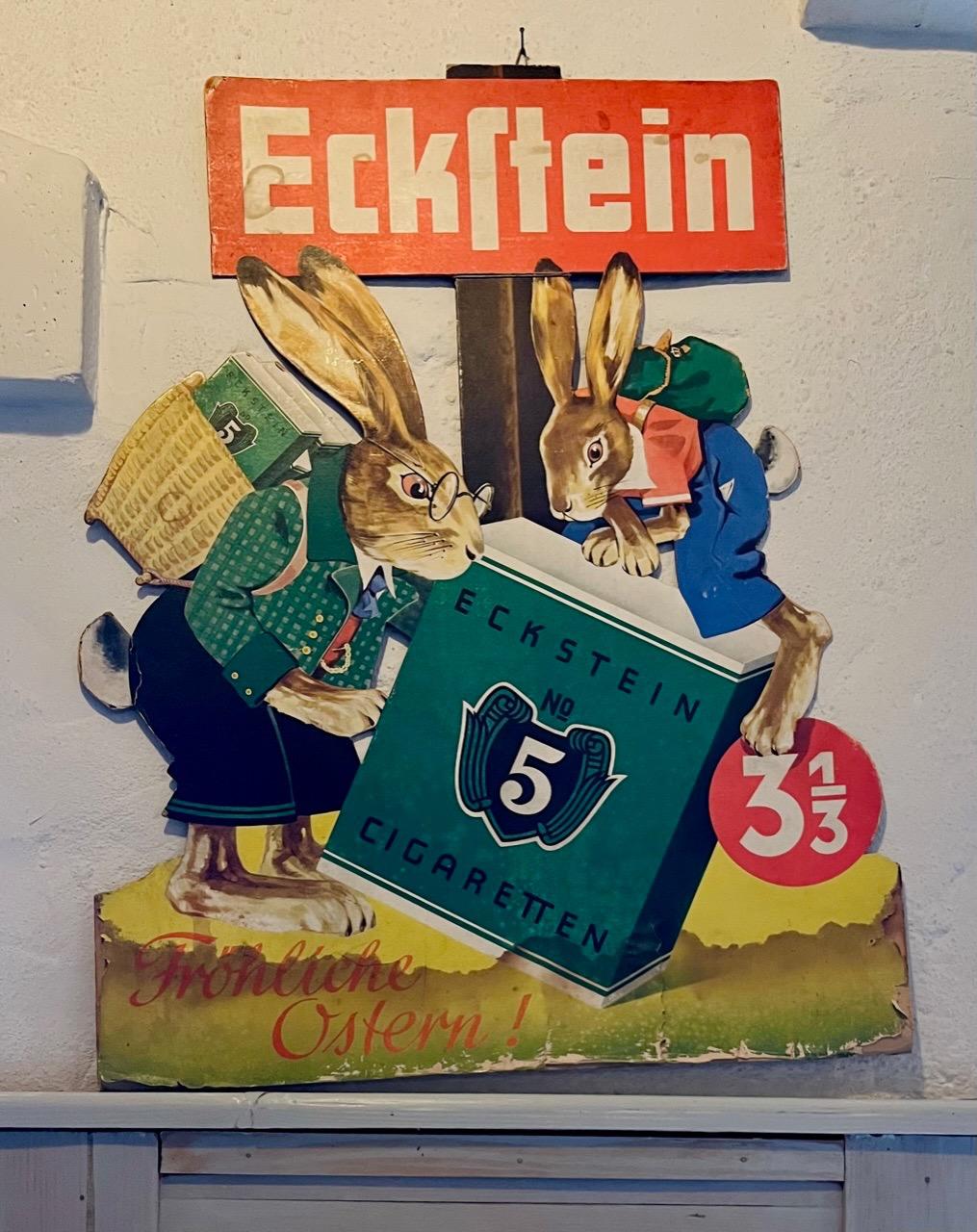
Die Verwirrung ist ganz in meinem Kopf.  Ich habe die echt unter Selectrix abgespeichert. Ich meine natürlich die IBM Selectric 😊
Aber vielleicht macht sich so ein Kugelkopf auch in einer Modellwelt ganz gut.
Fröhliche Ostern!
Eckstein. Das war schlimmes Zeug ohne Filter. Ich hatte mal einen Vermieter in den 90ern. Der hat davon viel geraucht, das war über Stockwerke kaum auszuhalten. Eckstein war damals angeblich schon schwer zu bekommen.
Eckstein gab es wohl noch bis 2015. Ich hab in meiner Jugend in den 1990ern auch mal ne Packung gekauft — aber das war ähnlich starker Tobak wie Karo.
Sind nun nicht alle wahnsinnig spannend, ich fand die Visitenkarten trotzdem ganz interessant. Auch wegen der Notizen …
Nachtrag: Die Visitenkarten waren in einer Ausstellung im Metropolitan Museum of Art / NY zu sehen (außer Warhol und Ed Ruscha).
Warum hier keine einzige Künstlerin vertreten ist, ist nachvollziehbar wohl der Zeit / dem Umstand geschuldet, dass die meisten vor dem 20. Jh. angefertigt worden sind … Nach Recherche habe ich allerdings praktisch überhaupt keine Visitenkarten berühmter Künstlerinnen gefunden.
Außer von Vivien Westwood und Coco Chanel, wobei letztere nur allgemein auf das Modehaus verweist …
Seltsam.
Gibt es eigentlich eine Bezeichnung für diese Form der 2?
Ich bin in letzter Zeit öfter darüber gestolpert ...
Ich überlege noch, ob ich's neunundzwanzig oder zweiundneunzig nennen soll, wahrscheinlich eine Sache des Standpunkts wie bei sechs versus neun ...